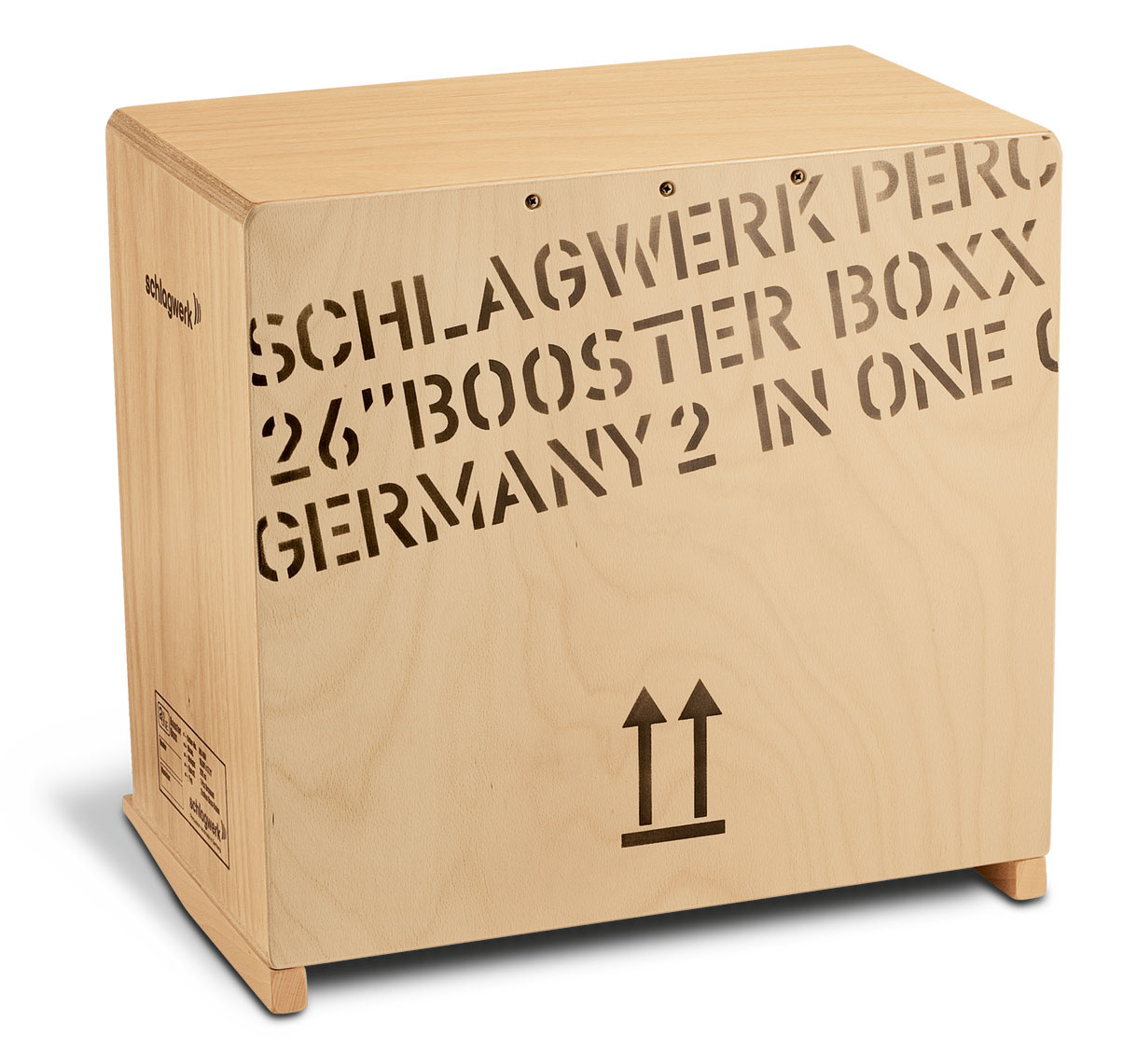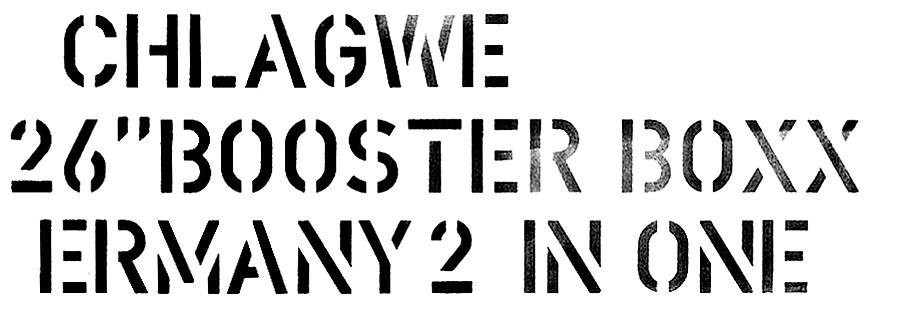
Welche DIN Stencil auf Schlagwerk-Cajon 2-in-one?
Schwierig?
Dafont, Myfonts und Fontsquirrel habe ich schon abgegrast (und dabei hoffentlich keine übersehen). Vielleicht hat man das auch selber gebaut? :-?
Habe das noch mal etwas entzerrt, falls das was nützt.
Auffällig sind halt die sehr breiten Aussparungen.
Nur als Hinweis: Bei neueren Produkten wird auch eine etwas andere Schrift mit schmäleren Stegen verwendet:
Das könnte die Schablonierschrift sein, ja. Wobei ich vermute, dass diese Beschriftung nur mangels der originalen entstanden ist …
Noch auffälliger ist der waagrechte Steg am Fuß der 2. Alle meine Schriftbeispiele zeigen einen senkrechten Steg im Fuß der 2 und bei der Suche auf Myfonts habe ich nur noch eine Schrift gefunden mit einem fast senkrechten Steg. Aber ein waagrechter Steg ist mir in etwa zwei dutzend Schriftmustern auf Platte und bei Myfonts nicht untergekommen.
Wirkt etwas in die Breite gezerrt, oder? Dann könnte es sogar die DIN Schablonierschrift sein: http://www.dafont.com/de/search.php?q=din+schablonierschrift&text=ID+SCHLAGWERK+BOX
Aber diese hat keinen waagrechten Steg im Fuß der 2, sondern einen senkrechten. Daher habe ich diese nicht als Lösung gesehen und Deine Anfrage  erst mal abonniert, um zu schauen ob andere Forenten schlauer sind als ich.